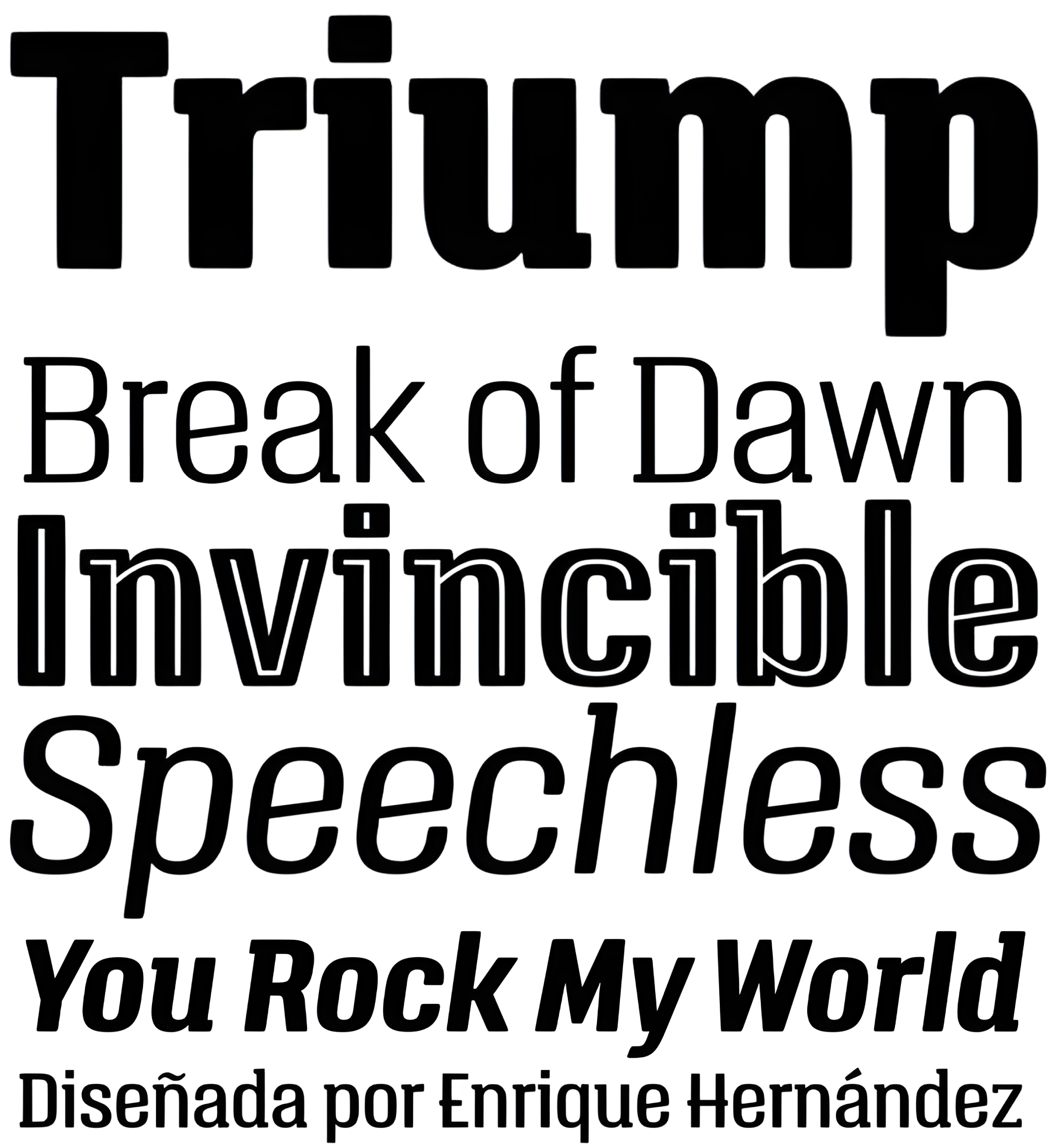
| Año | 2014 |
| Créditos | Enrique Hernández |
| Descripción | La familia tipográfica Triump es una sencilla sans serif con 6 pesos, desde Thin, ideal para usar como epígrafe, hasta Black para títulos de especial impacto. Excelente para aplicar en diseño gráfico como logotipos, marcas, carteles, diseño editorial y web. Inspirada en los tipos clásicos de finales del siglo XX con esquinas redondeadas que dan a la tipografía un aspecto suave con extremos redondeados, con un trazo horizontal que supera al vertical en las letras A, E, F, H, J y K lo que le confiere una marcada personalidad. Triump viene con un peso Negro en línea normal y cursiva tanto en mayúsculas como en minúsculas, especial para dar un aspecto vintage a los diseños. |
| Familia(s) | Thin, Thin Italic, Light, Light Italic, Regular, Regular Italic, Bold, Bold Italic, ExtraBold, ExtraBold Italic, Black, Black Italic, Black Inline, Black Inline Italic |
| Estilos | 14 |